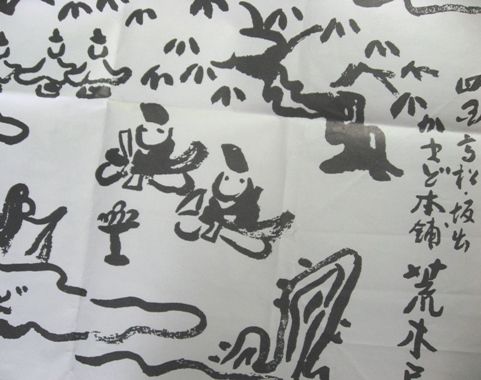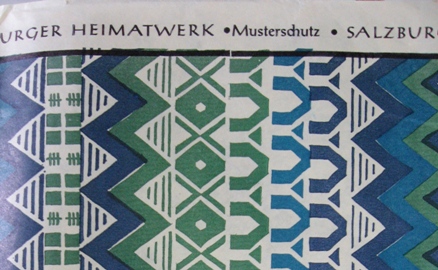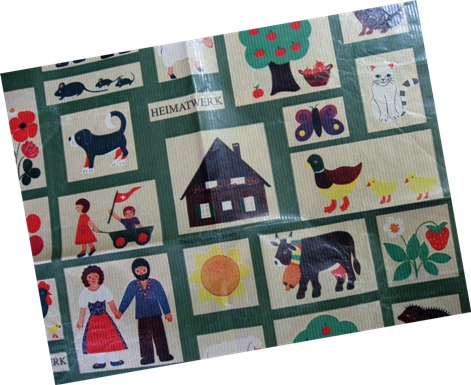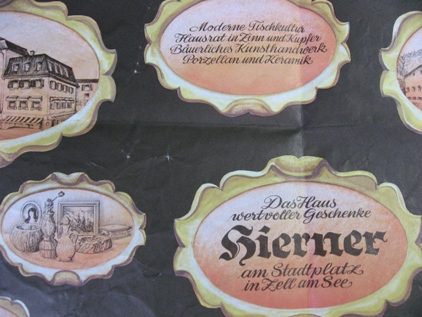
また、紙が・・・。
何だ、何だと中を見ると・・・「ぅわ!また紙が・・・!」
どこかで包んでもらったラッピングペーパーは、
こうして時を経て現れたのでした・・・。
これは、おしゃれですね。エッチングの作品がデザインに
入っています。
あら〜、このお店は創業1875年だったんだわ・・・。何を買ったのか忘れてましたが、
中の絵とPorzellanという文字を見て・・・「あっ!エッグスタンド」・・・何気ない絵にヒントが入っていて
素敵です。文字もこのお店の雰囲気とすごくあってたな〜って改めて思いました。
これは「HEIMARTWERK」・・・ご当地での手工芸品ですね。
このラッピングペーパーには、ちゃんとこの絵のデザイナーさん
の名前が印刷されていました。
K. Kiener、スイスの人みたいです。素朴な感じをうまく出して
いますね。
これも「HEIMARTWERK」
でもザルツブルグと印刷されて
います。
織物のような模様と色が
上品で素敵です。
文字もデザインに合った感じで・・・だから捨てないで
とってあったのかも・・・。
スイスもオーストリアも手作り感を十分に表現している
デザインかと思います。本当にステキ!!
これは、これは・・・あの話題の「かまど」です。
(一部、ブログでは話題になっております・・・はい)
ミョーチクリンな感じがかわいいです。
こちらも日本の素朴感で、あの和菓子の雰囲気と
合っている気がします。
整理してるのに・・・捨てられない・・・。
捨てられないほど可愛いデザインを考えるデザイナーさん・・・尊敬ですね。